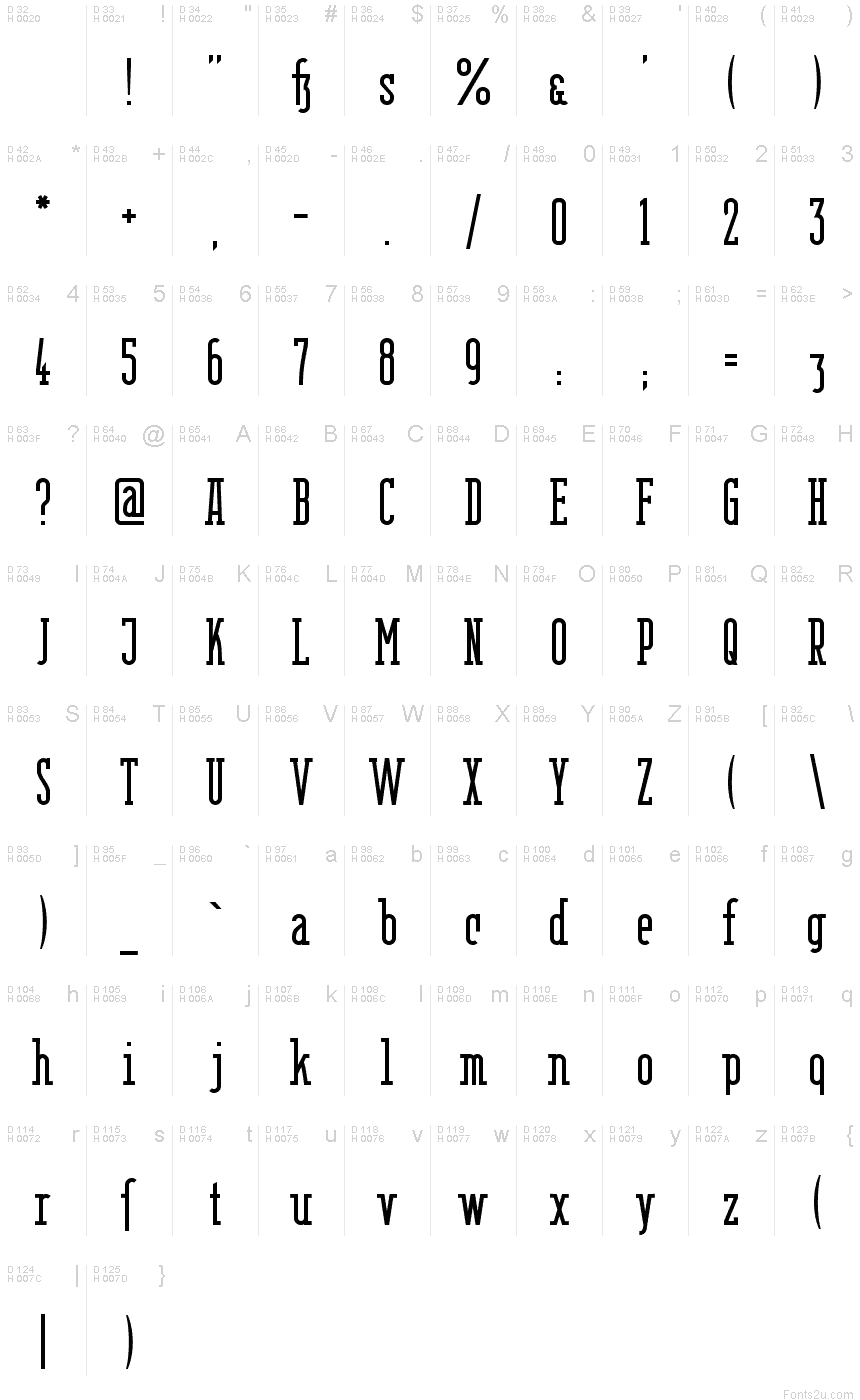
Berlin Email Serif von Peter Wiegel ist eine kostenlose Serifenschrift im Jugendstil mit hohen, schmalen Buchstaben und dem Flair von Postern aus dem frühen 20. Jahrhundert. Der starke vertikale Rhythmus, die gekappten Serifen und die abgerundeten Kleinbuchstaben verleihen ihr einen kompakten, urbanen Charakter, der sowohl förmlich als auch leicht exzentrisch wirkt.
Sie passt perfekt auf Buchcover, für Kabarett- oder Theaterplakate, in die Gastronomie, für redaktionelle Überschriften und Titeltafeln, bei denen das historische Flair wichtiger ist als Neutralität. Da es sich um eine kostenlose Schrift handelt, eignet sie sich zudem hervorragend für kurze Namen auf Verpackungen, Veranstaltungsflyer oder Menükarten, da die kondensierte Form es erlaubt, Texte platzsparend unterzubringen, ohne die Stimmung zu beeinträchtigen.